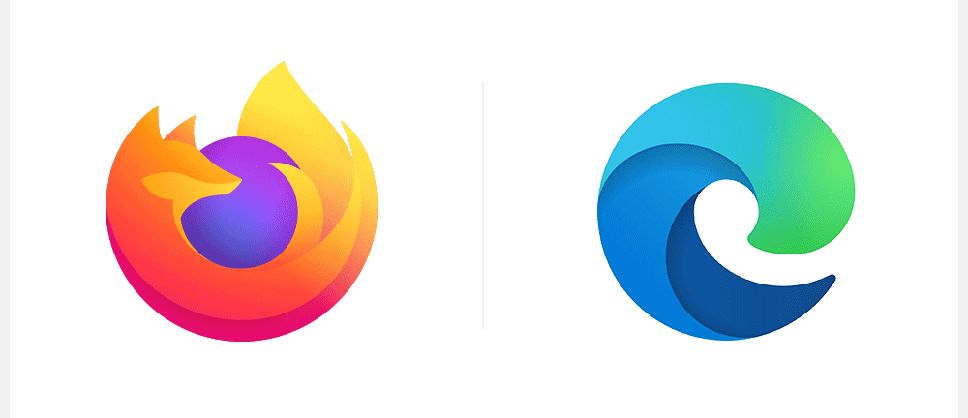
IE浏览器新logo正式上线, Microsoft Edge 浏览器启用新logo
在这个全球互联的时代,我们天天都在跟浏览器打交道。这里不得不说到微软了,去年底,微软更新了Office产品logo的设计,包括Word、Excel和PowerPoint的新图标设计。近日,有媒体曝光,微软即将要对基于Chromium打造的Edge浏览器更换新logo。
我们发现Edge的新logo形状继续基于小写字母e来做设计,整体外观类似于波浪造型,底部为蓝色,顶部为绿色。这样的设计无论颜色还是图形,完全摆脱了Internet Explorer 的影响和束缚,因此看起来更加美观时尚,不过这是否也借鉴了火狐的设计思路呢?接下来让我们一起欣赏Internet Explorer图标LOGO设计的演变过程吧!